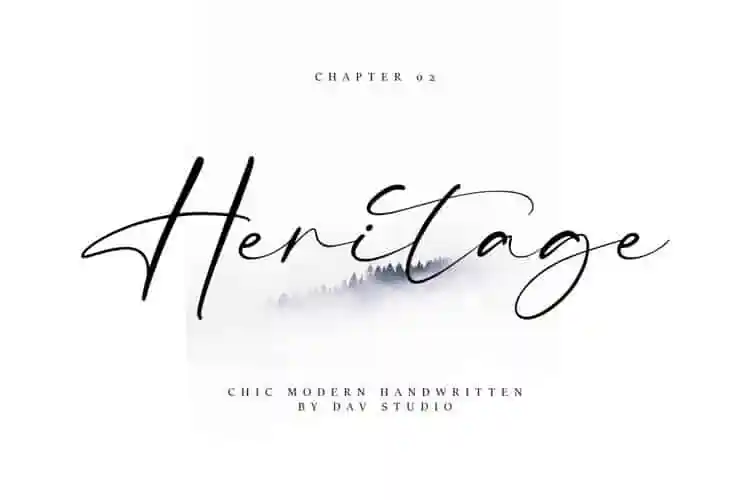
A Heritage Script Font é uma fonte criada à mão pelo Dav Studio, com alternativas minúsculas e ligaturas para oferecer flexibilidade adicional. Inspirada na natureza do dia-a-dia, ela captura a leve feminilidade de manhãs contemplativos, tornando-se perfeita para o próximo projeto design. Heritage Script é um fonte suave e belo que retrata as habilidades únicas e elegantes dos artistas da letra à mão. Suas letras são limpas e bem equilibradas, atendendo às necessidades de qualquer projeto gráfico. Adicione a sua criatividade mais audaciosa e observe como ela transforma suas ideias em realidade. Esta fonte é perfeita para aqueles projetos que precisam de uma escrita elegante e sofisticada, mas também convidativa e acessível à mesma vez. Tornando-se um recurso valioso para designers que buscam expressar seus trabalhos com um toque pessoal e aprimorado. Com Morning View em destaque, Heritage Script é uma opção sólida para qualquer projeto de design digital.